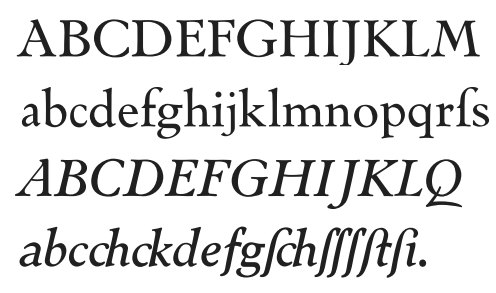
(Slab-)Serif mit bedingten Ligaturen und hoher Oberlänge
Bin auf der suche nach einer (Slab-)Serif mit zahlreichen bedingten Ligaturen und hoher Oberlänge.
st sollte schon drin sein und es muss nicht unbedingt eine slabserif sein.
Was auch schön wäre, wenn das a im kursiv-Schnitt in der offenen Variante bleibt. So wie beispielsweise bei der Museo Slab. Die bietet jedoch leider keine bedingten Ligaturen.
Mir fällt nur die FF Nexus sowie FF Scala und FF Seria ein, wobei die auch nicht die Kriterien des a erfüllen.
Vielleicht hat ja jemand noch ein paar Alternativen.
slab + hohe oberlänge + offenes a =
wobei ich da jetzt nicht auf anhieb weiss wie es mit den ligaturen aussieht.
sehe gerade du wolltest das offene a in der kursiven, ich glaube das ist bei
der neutraface nicht möglich.
Ich würde mich schon mit einer Slabserif mit offenem kursiven a zufrieden geben… Danke für die Neutraface, da sind mir sie allerdings schon ein wenig zu hoch : )
Eine Caecilia kommt der Sache auch schon näher allerdings sind mir da die Oberlängen ein wenig knapp bemessen und der eckige i Punkt gefällt mir nicht so gut.
Fällt jemand eine Schrift im Duktus der Garamond, mit offenem a in der kursive und vielleicht ein bisschen »moderner« ein?
Gibt es denn keine Suchmaschine mit der man nach bestimmten Eigenschaften suchen kann?